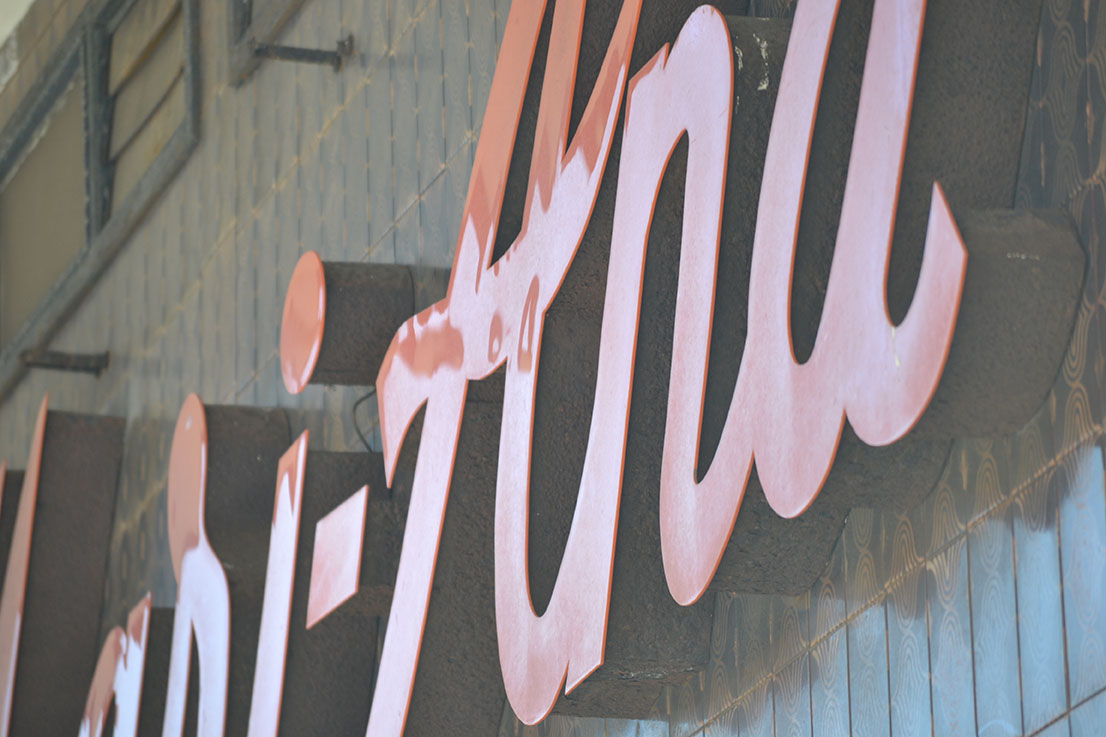
Finales de los 70
[/wyde_info_box][wyde_info_box title=»Estado» icon_set=»typicons» icon_typicons=»typcn typcn-eye»]Permanece[/wyde_info_box]
[wyde_info_box title=»Tipografía» icon_set=»typicons» icon_typicons=»typcn typcn-sort-alphabetically»]Script[/wyde_info_box][wyde_info_box title=»Técnica» icon_set=»typicons» icon_typicons=»typcn typcn-brush»]PVC[/wyde_info_box]
Calle Camilo Alonso Vega, 26. Santander
Un gran rótulo que está «escondido» en la calle Camilo Alonso Vega, con una tipo script en naranja. En la puerta está rotulado en pan de oro el nombre con una variación de la tipo. También se puede observar otra variación del nombre en la esquina sobre fondo rojo.
Es de los pocos rótulos que permanecen intactos de esas dimensiones en un negocio aún abierto y casi clásico en la ciudad. Nos comentaron que tuvieron que retirar una placa-anuncio de más de treinta años por obligación.